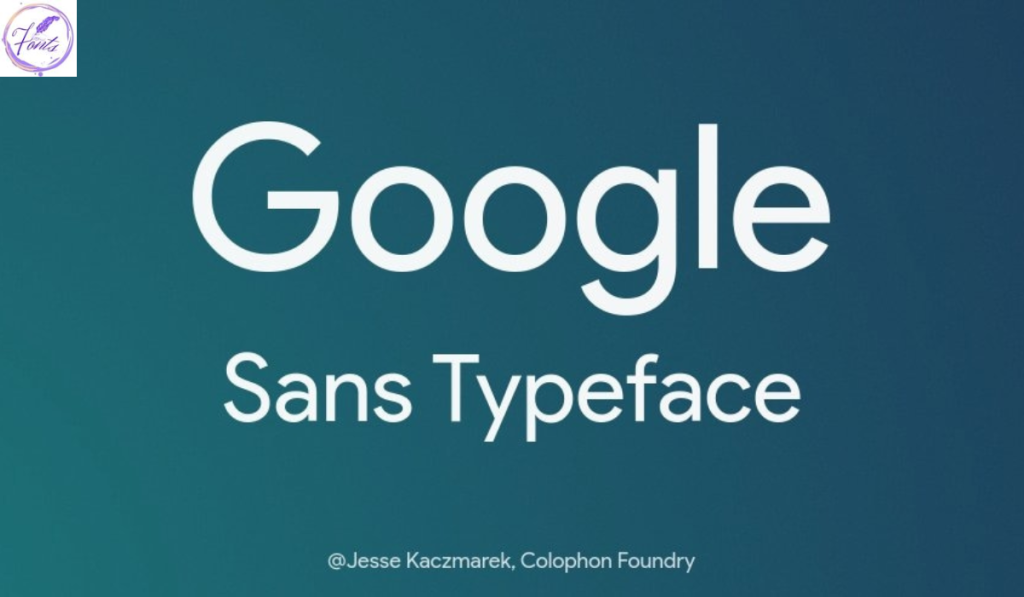
Bộ Font: Google Sans
Phân loại: Hiện đại, Thanh lịch, Cân đối, Dễ đọc
Kiểu chữ: Không chân
Trong thế giới thiết kế đồ họa, font Google Sans nổi bật với thiết kế hiện đại và tối giản, tạo nên một hình ảnh sạch sẽ và chuyên nghiệp. Đây là phiên bản được phát triển từ font Product Sans, được Google sử dụng rộng rãi trong các sản phẩm và dịch vụ của họ. Với sự việt hóa đầy đủ, font Google Sans mang đến cho người dùng tiếng Việt một trải nghiệm đồng nhất và thân thiện, phù hợp với mọi ứng dụng từ in ấn đến thiết kế web.
Đánh giá font google sans
Font Google Sans nhận được đánh giá cao nhờ vào sự kết hợp giữa vẻ ngoài thanh lịch và độ dễ đọc cao. Font này được đánh giá là một trong những lựa chọn hàng đầu cho các nhà thiết kế và nhà phát triển bởi tính ứng dụng rộng rãi và khả năng tương thích cao. Đặc biệt, với phiên bản việt hóa, font Google Sans còn góp phần lan tỏa ngôn ngữ và văn hóa Việt trong không gian số. Sự tối giản nhưng không kém phần hiện đại của font này làm cho nó trở thành một phần không thể thiếu trong bộ công cụ của mọi nhà thiết kế.